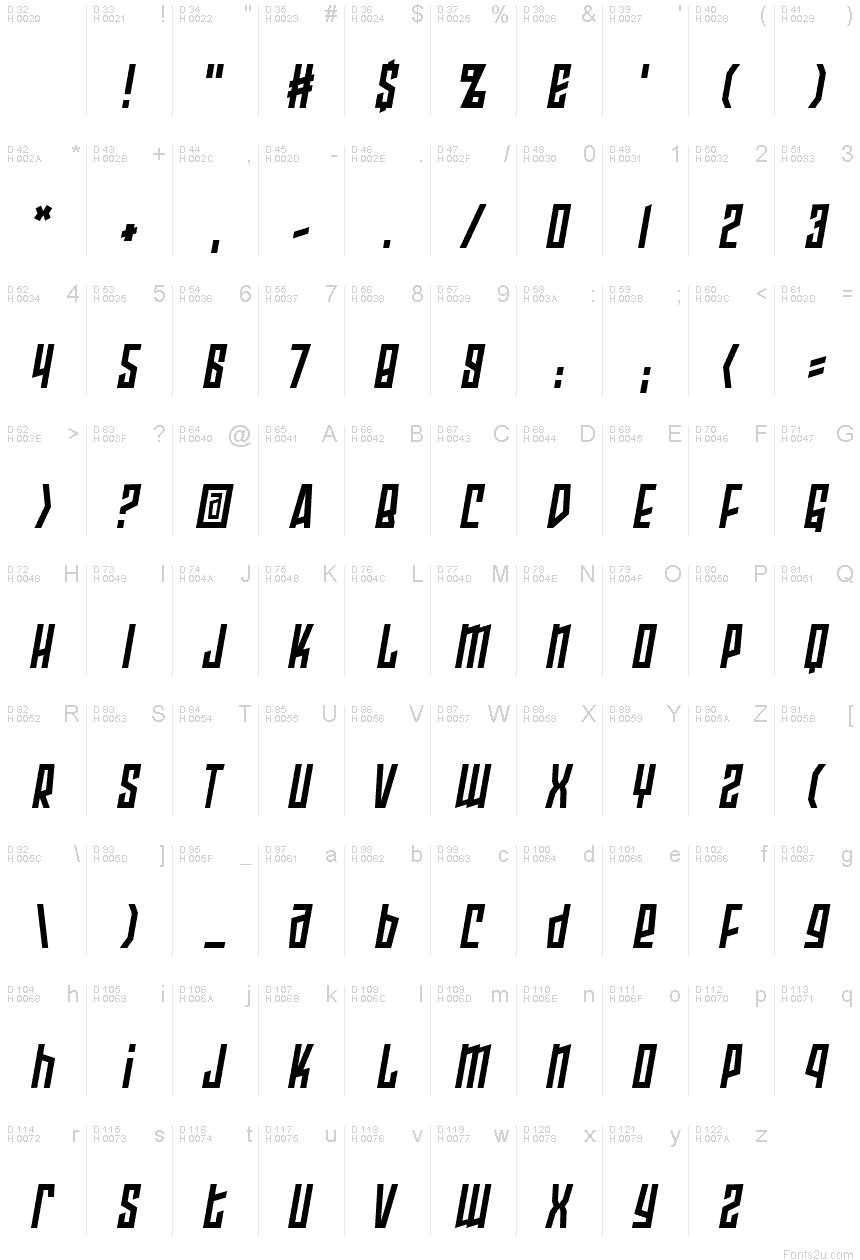
Armor Piercing 2.0 BB Italic
Armor Piercing 2.0 BB Italic autorstwa Nate’a Piekosa to darmowy font techno typu display z rodziny Armor Piercing 2.0 BB. Pędzi naprzód z ostrym nachyleniem, kwadratowymi krzywymi i ciasnym, mechanicznym światłem, wyglądając jak wycięty w metalu – czysty, szybki i nieco niebezpieczny. Kreski uderzają z siłą, nadając krótkim hasłom natychmiastowej dynamiki.
Dzięki Armor Piercing 2.0 BB Italic nagłówki zyskują wyrazistość na okładkach komiksów, plakatach sci-fi, w interfejsach gier, logotypach e-sportowych, ulotkach technologicznych, miniaturach YouTube i naklejkach. Ten darmowy font najlepiej sprawdza się w wielkich literach lub kompaktowych tytułach, gdzie jego kanciasty rytm jest czytelny na pierwszy rzut oka. Zestaw go z neutralnym krojem bezszeryfowym w tekście głównym i daj mu odetchnąć w większych rozmiarach.